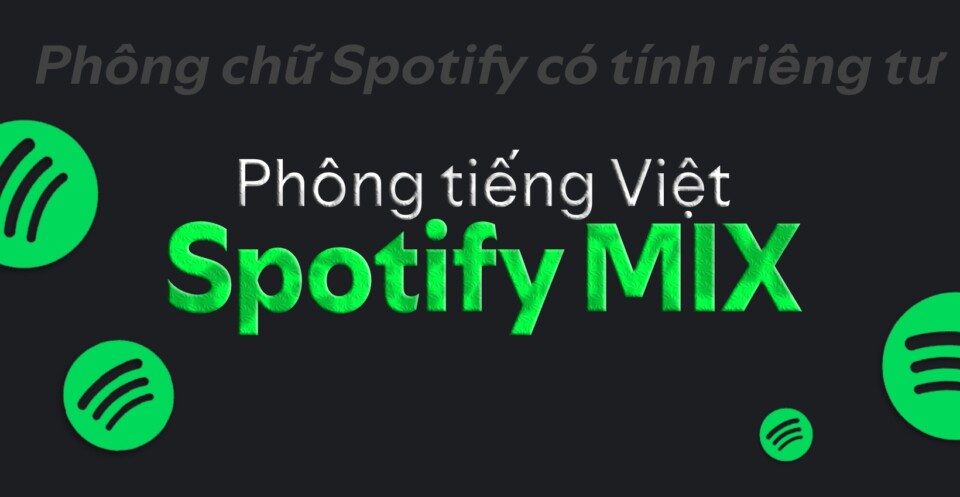
Giới thiệu về Font Spotify Mix Việt hóa (5 files)
Chào mừng bạn đến với thế giới sáng tạo nơi những con chữ truyền tải cảm xúc. Font Miễn Phí hôm nay xin giới thiệu bộ Font Spotify Mix Việt hóa (5 files), một giải pháp thiết kế chuyên nghiệp được lấy cảm hứng từ nhận diện thương hiệu âm nhạc hàng đầu thế giới. Đây là bộ font chữ độc đáo, kết hợp hài hòa giữa phong cách hình học hiện đại và những nét cổ điển tinh tế. Với khả năng tương thích cao, bộ phông này giúp mọi văn bản trở nên sống động và dễ đọc hơn bao giờ hết trên các thiết bị kỹ thuật số hiện nay.
Đặc điểm nổi bật của Font Spotify Mix Việt hóa (5 files)
Tính ứng dụng linh hoạt trong học tập
Bộ Font Spotify Mix Việt hóa (5 files) bao gồm 5 trọng lượng khác nhau, từ nét thanh mảnh đến nét đậm bản lớn. Điều này cực kỳ hữu ích cho các bạn học sinh khi trình bày bài thuyết trình hoặc làm báo cáo dự án. Sự rõ ràng của các ký tự giúp người xem dễ dàng tiếp nhận thông tin mà không gây mỏi mắt. Đặc biệt, phiên bản Việt hóa đã được tối ưu hóa hoàn toàn hệ thống dấu câu, đảm bảo không xảy ra lỗi hiển thị khi soạn thảo văn bản tiếng Việt phức tạp.
Vẻ đẹp hiện đại cho thiết kế đồ họa
Không chỉ dừng lại ở văn bản thuần túy, bộ font này còn là trợ thủ đắc lực cho việc thiết kế poster, banner hay ảnh bìa mạng xã hội. Phong cách thiết kế của Spotify Mix mang lại cảm giác trẻ trung, năng động và đầy năng lượng tích cực. Bạn có thể dễ dàng phối hợp các tệp tin trong bộ 5 files để tạo ra sự phân cấp thông tin rõ ràng, giúp tác phẩm của mình trở nên chuyên nghiệp như những nhà thiết kế thực thụ.